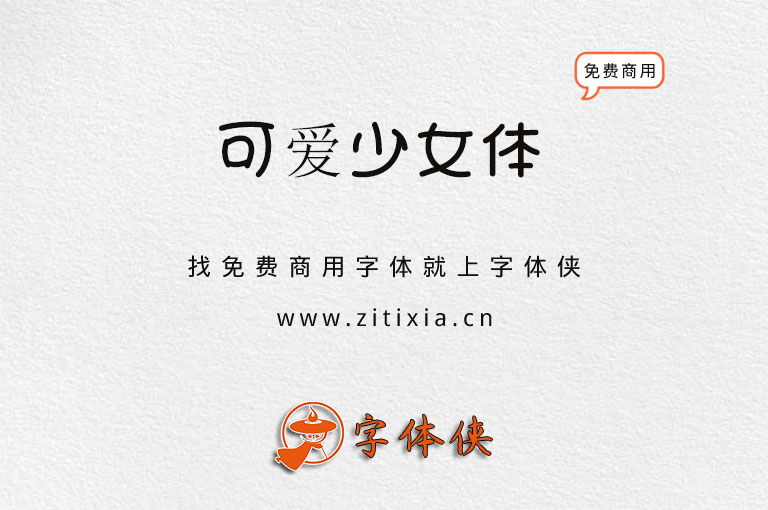
可爱少女体字体简介:
这是一款来自日本的非常可爱的字体, 「 可爱少女体 」(日文名:ポプらむ☆キュート ) 。支持的汉字不算特别多,这是比较可惜的。但是其可爱的字型还是让人爱不惜手,喜欢这套字体的朋友们可以一试哦。说不定刚好有你想要的字体呢。
「 可爱少女体 」 收录汉字约3200个 (JIS第1水准2965字,第2水准260字)
字体名称:ポプらむ☆キュート